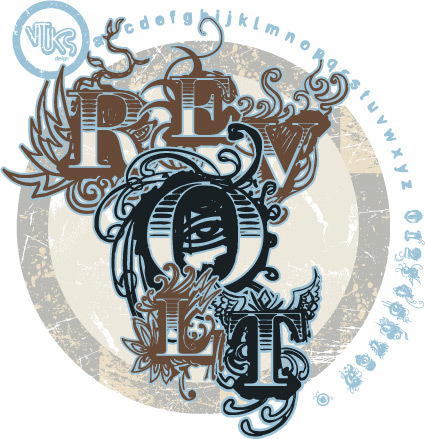
Vtks Revolt, di Douglas Vitkauskas, è un font gotico gratuito per iniziali, caratterizzato da lettere dense e ribelli con ricchi fregi incisi. Le forme decorate accostano interni a righe pesanti a viticci sinuosi e tratti spinosi, mentre le lettere più semplici mantengono un peso grezzo, come se fossero intagliate a mano.
È perfetto per copertine di album metal, branding di studi di tatuaggi, poster di eventi occulti, testate di fanzine e titoli dark fantasy. Come font gratuito, dà il meglio di sé in contesti brevi e di forte impatto, dove i suoi riccioli elaborati e le forme solide hanno spazio per respirare e una singola parola può reggere l'intera composizione.